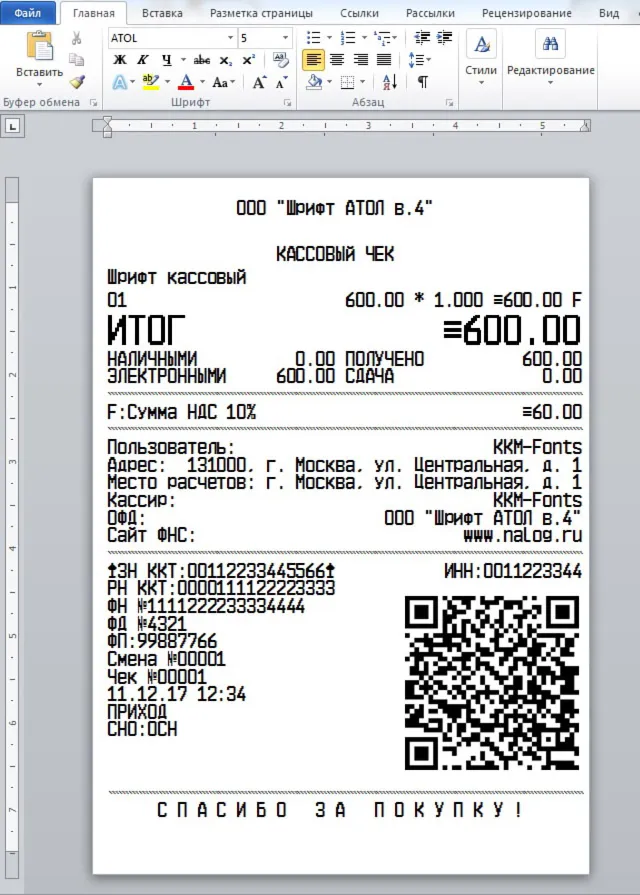
Шрифт ККМ АТОЛ в.4(ttf)
Распространенный шрифт в семействе кассовых аппаратов и фискальных регистраторов АТОЛ в формате TTF (русские и английские буквы) для использования в программе Microsoft Word, а так же в любых других текстовых редакторах. В архиве находятся шрифт в формате TTF и шаблон чека. Вам остается только установить шрифт в систему (обычно C:\WINDOWS\Fonts), открыть шаблон и начать редактирование. Печатать чеки предпочтительно на термопринтере, как, например, CITIZEN-S310, на кассовой термоленте. Хотя можно печатать и на струйнике и лазерном, с возможностью вывода на факсовую бумагу. Лучшее качество, естественно, при печати на термопринтерах.